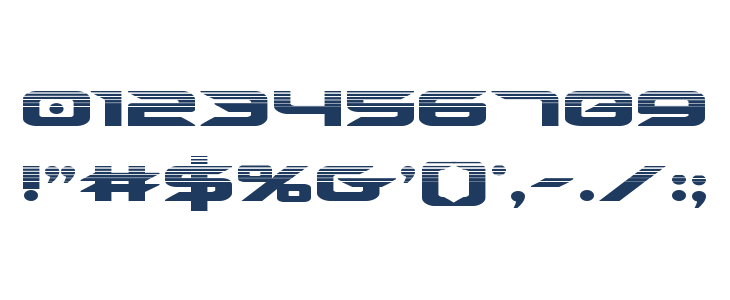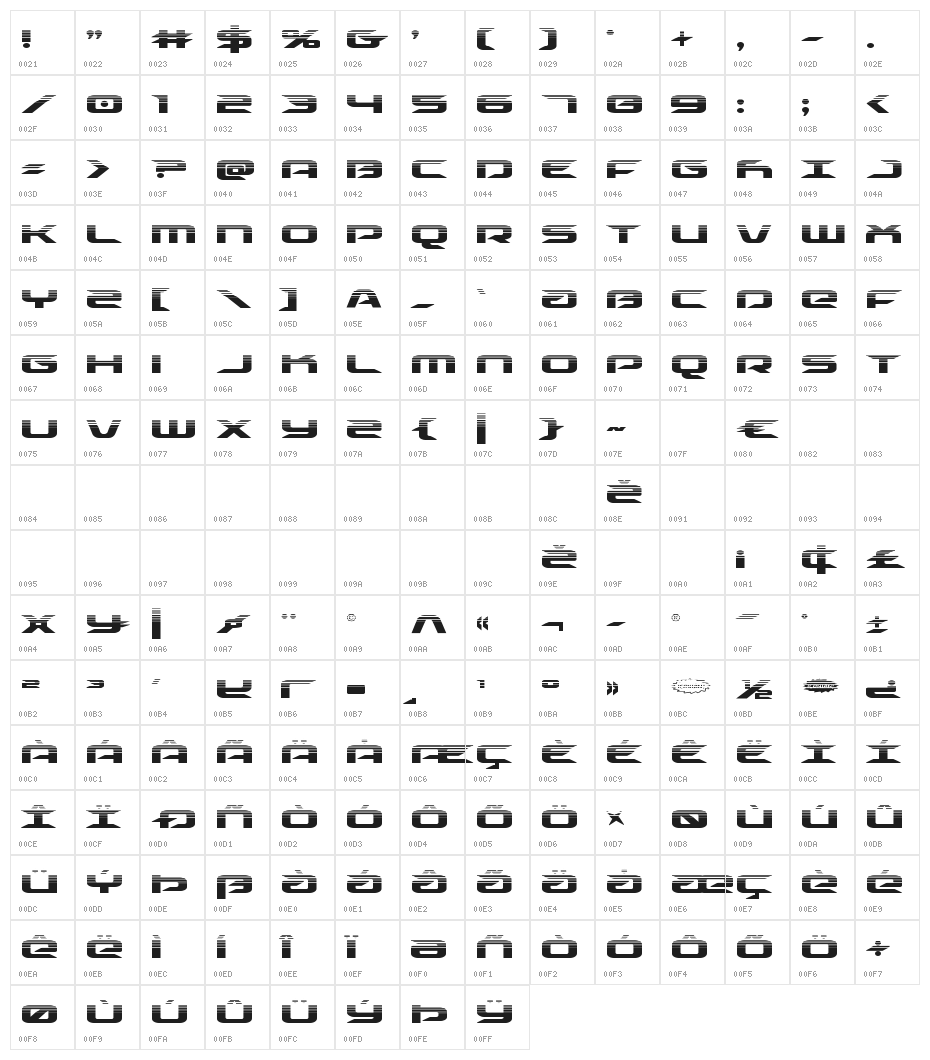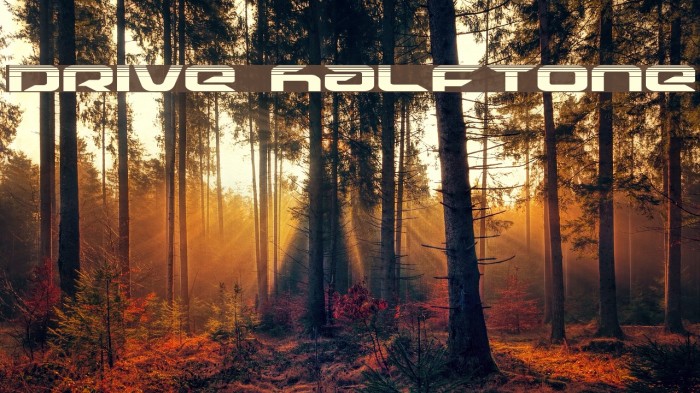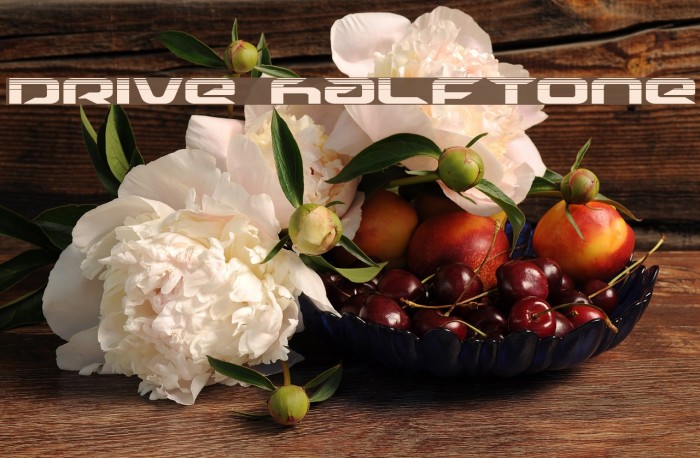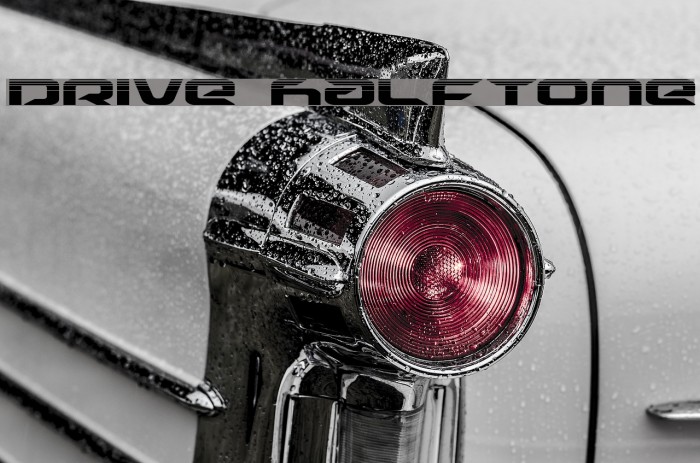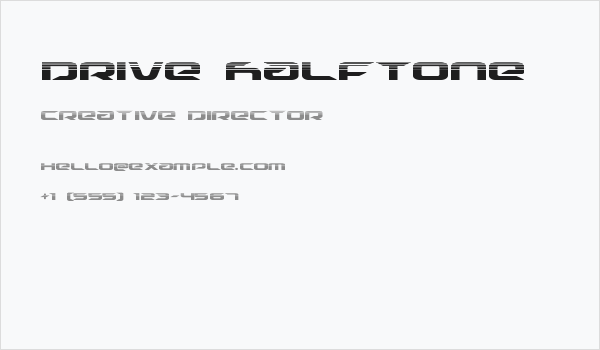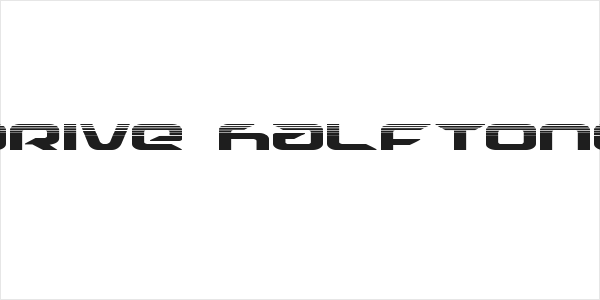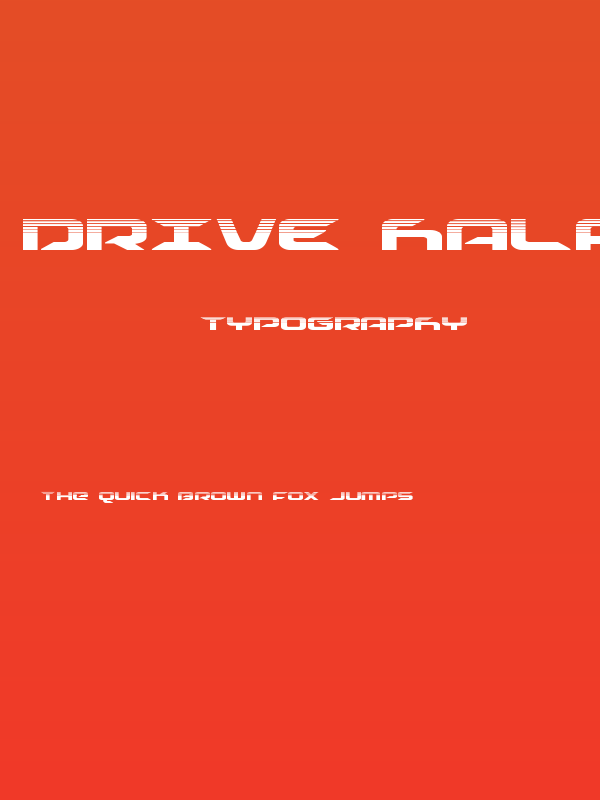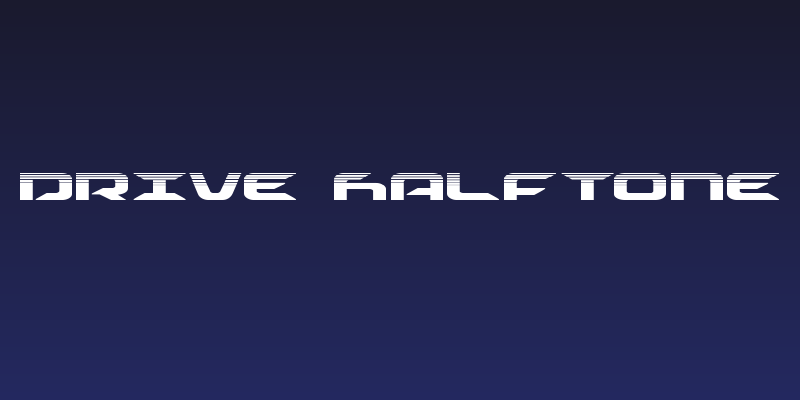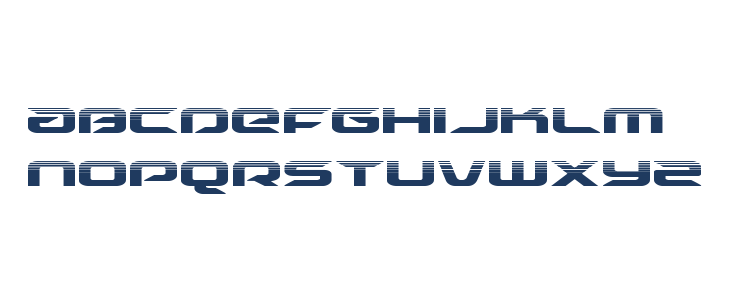
Drive Halftone Font
| Ancho | Expanded |
| Proyectos propuestos | Ideal for sci-fi themed designs, video game titles, tech branding, and futuristic posters. |